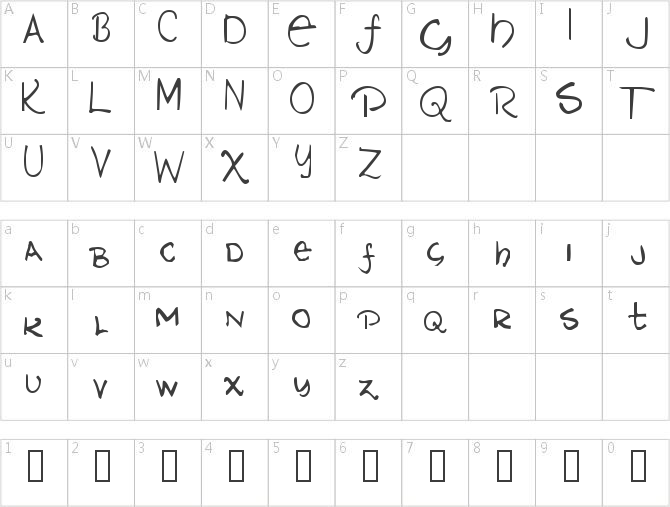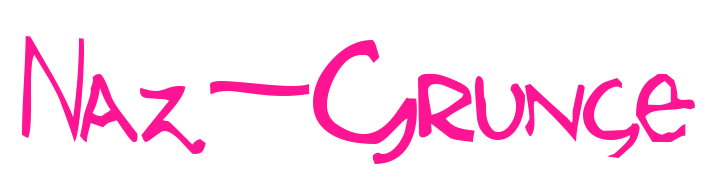
Naz-Grunge 詳情頁
字體名稱: Naz-Gru
Naz-Grunge
Naz-Grunge介紹
Naz-Grunge字體字庫是一款讓人賞心悅目、百看不厭的英文字體,適合各類廣告和產(chǎn)品包裝設(shè)計應(yīng)用,字體大小0.02MB,格式為ttf字體,上傳用戶是浪遍塞納河的,作者/版權(quán)方為未知